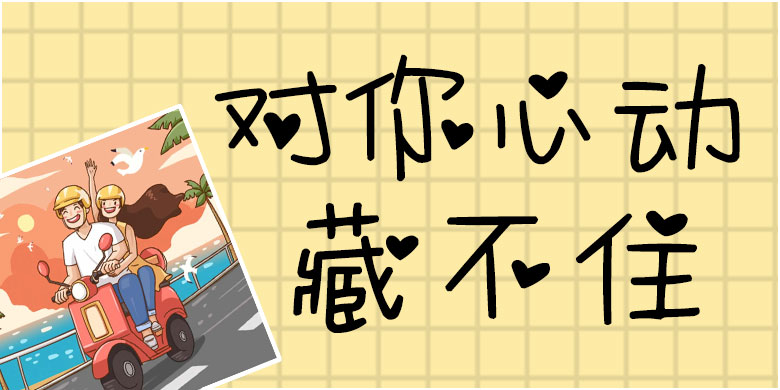
方正手迹-对你心动藏不住
方正手迹-对你心动藏不住,这款字体结构工整、笔画清晰,兼顾美观与易读性,适用于标题、正文、海报、包装、LOGO 等多种场景。字形优雅稳定,风格百搭耐看,适配日常排版与创意设计,让文字呈现更舒适、更具质感。方正手迹-对你心动藏不住一笔一画,皆是细节,以均衡的比例、流畅的线条打造舒适视觉体验,字形端正大气,风格简约现代。无论是商业设计、品牌宣传还是日常排版,都能轻松驾驭,让文字更有格调与力量。方正手迹-对你心动藏不住字体下载。
字体品牌: 方正手迹 设计师:俞亦婷 字体分类:创意书写 字体属性:精品字 字符集:大陆简体(GB2312-80) 发布时间: 2019
对你心动藏不住字形可爱,爱心元素的加入,使对你心动藏不住具有鲜明的甜美可爱特质。适用于萌宠类的书刊、品牌广告和产品包装设计,以及社交网络的个性化用字。